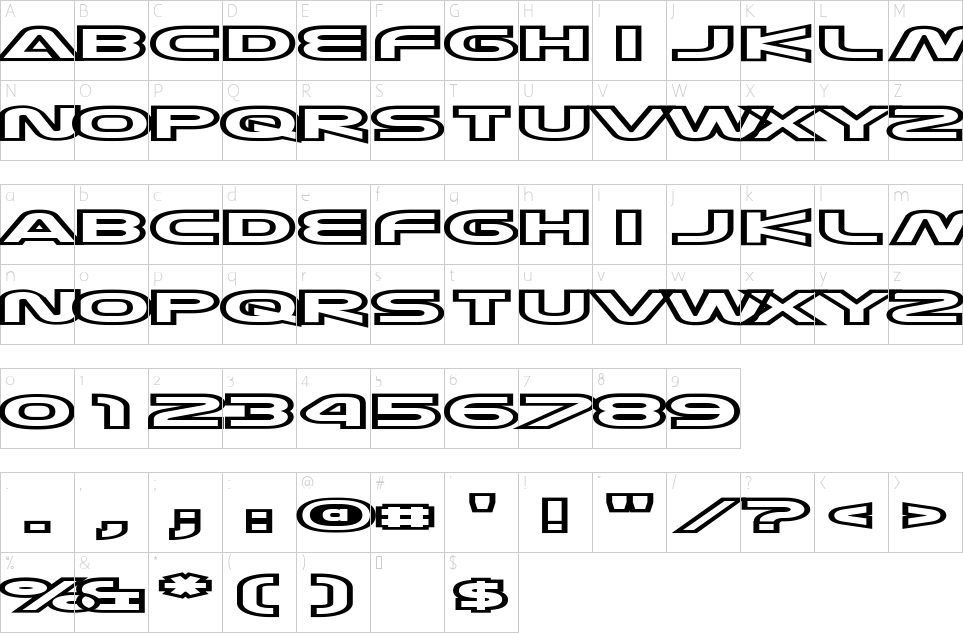
A fonte Joy Circuit é uma escolha ótima para qualquer designer que busca uma fonte moderna e futurista para seus projetos digitais. Desenvolvida pela Typodermic Fonts, essa fonte moderna possui um design limpo e minimalista, com linhas arredondadas e traços levemente irregulares que a tornam ideal para aplicações em aplicações online, websites e aplicativos. Se você está procurando uma fonte que se destaca em seu design, sem perder a simplicidade e facilidade de uso, Joy Circuit é uma ótima opção. Com sua alta popularidade entre os usuários, você pode baixar a fonte Joy Circuit para Windows e Mac de uma forma fácil e rápida, tornando-a uma fonte indispensável para qualquer designer gráfico.